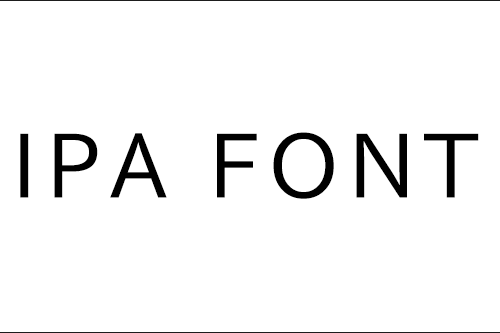
商用利用可能なIPAフォント10選まとめ
IPA Pゴシック
「JIS X 0213:2004」をサポートし、商用・非商用に限らず無償で利用できる高品位な日本語フォントのゴシック体。
IPA P明朝
「JIS X 0213:2004」をサポートし、商用・非商用に限らず無償で利用できる高品位な日本語フォントの明朝体。
IPAゴシック
“JIS X 0213:2004”をサポートし、商用・非商用に限らず無償で利用できる高品位な日本語フォントのゴシック体。
IPA明朝
“JIS X 0213:2004”をサポートし、商用・非商用に限らず無償で利用できる高品位な日本語フォントの明朝体。
あおぞら明朝
7ウェイト展開のIPA明朝ベースの明朝体フォント。
はんなり明朝
やさしくて、ふんわりとした、ひらがなとカタカナをデザインしたフォント。
フロップデザインフォント
水平、垂直の線がデザインの基本となっているシンプルなゴシック体の日本語フォント。
やさしさアンチック
ゴシック体の漢字にあわせた太い明朝体の「かな」が組み合わされたフォント。普通のアンチック体よりも太さの差が少ないので漢字との統一感が高い漫画用フォントにオススメです。
やさしさゴシック
ほんのり手書きの味わいとデジタルの見やすさが融合したフォント。
やさしさゴシック手書き
やさしさゴシックに手書きの風合いを加えた、少しガタガタした線のフォント。